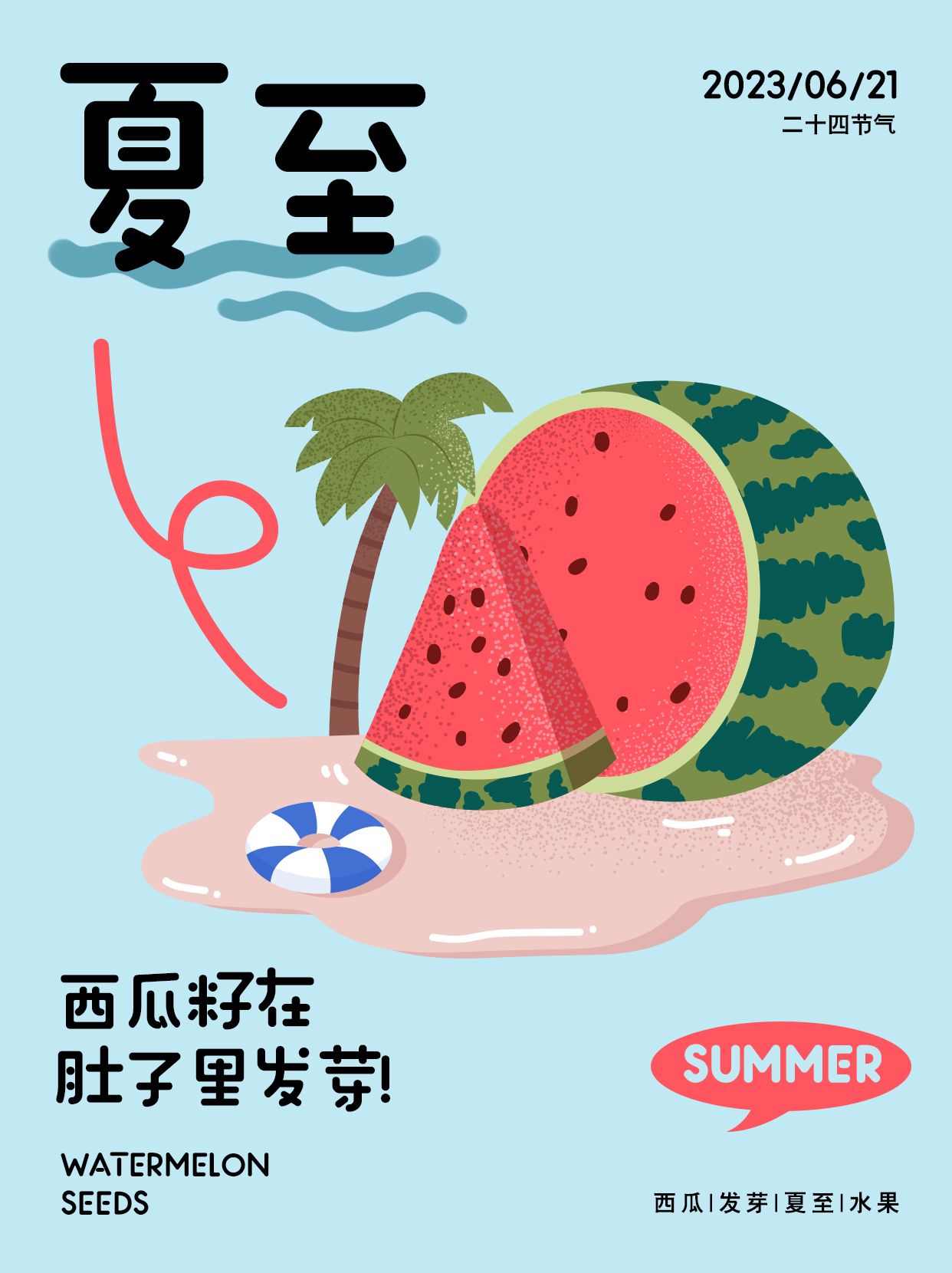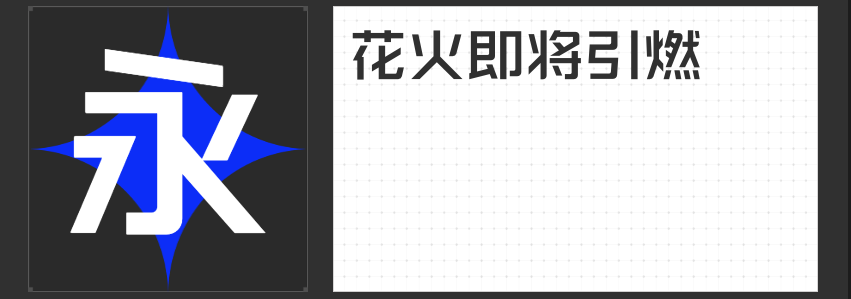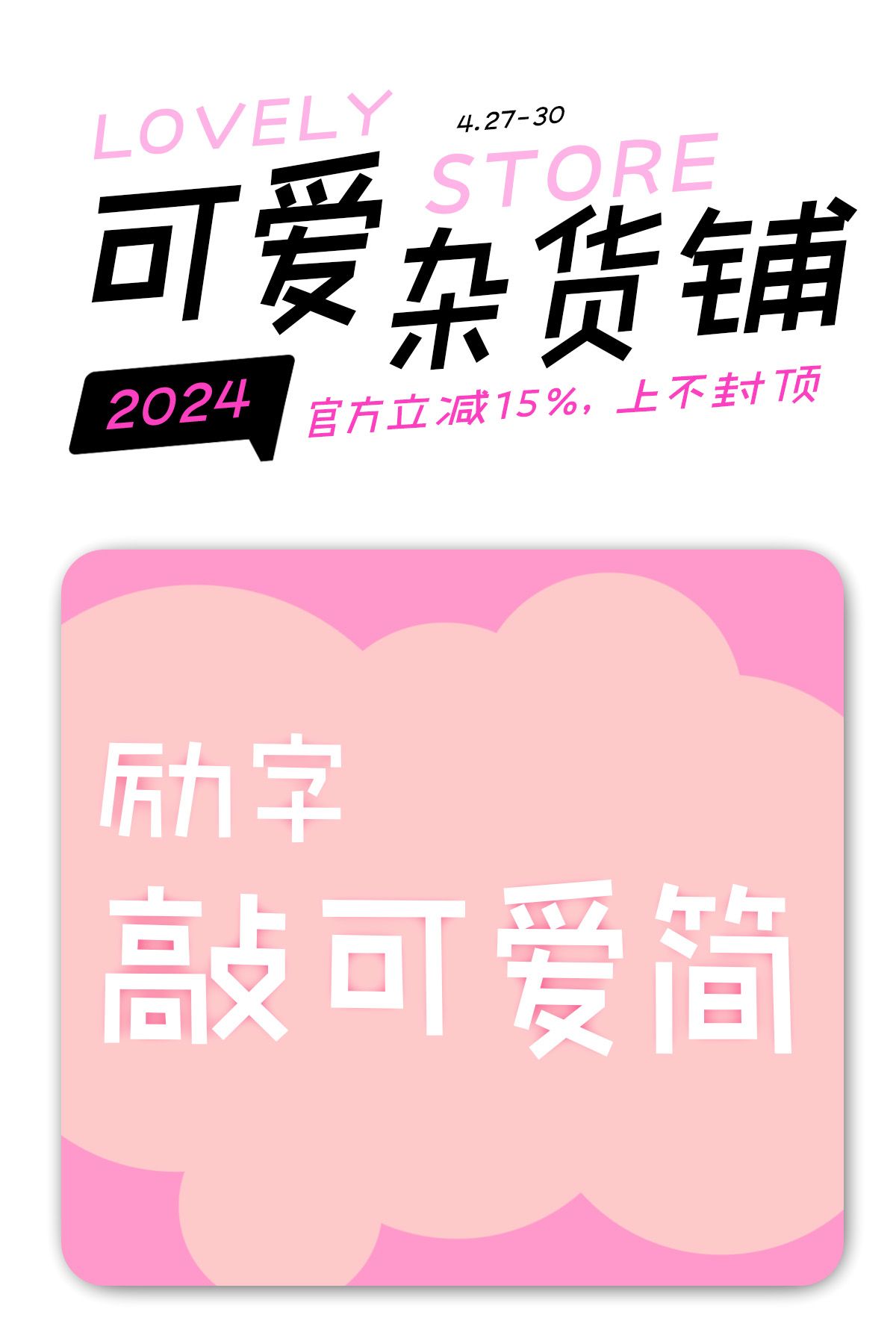
影视设计中的创意字体推荐:打造视觉盛宴的必备之选
在影视设计中,字体选择至关重要,它不仅影响着观众的阅读体验,更能营造出独特的视觉氛围。今天,我们为大家推荐四款专为影视设计而生的创意字体,它们各具特色,能够为影视作品增添无限魅力。
这款字体略带俏皮,充满趣味与想象。其手写的圆润线条在保留辨识度的前提下,省略了部分笔画,使得整体看起来简单明快,独具形式感。这种字体营造了一种用心书写的随性氛围,让影视作品中的文字更具手绘感和温暖度。无论是用于片头字幕、旁白还是角色对话,都能瞬间吸引观众的眼球。
这款字体笔划粗壮有力,没有衬线装饰,撇捺等笔画不尖,使得整体易于阅读且突出醒目。它常用于标题、导语和标志等场合,能够迅速抓住观众的注意力。在影视设计中,励字勇敢黑简 中黑不仅能够提升作品的层次感,还能增强视觉冲击力,让观众在观影过程中留下深刻印象。
这款字体拥有完美的斜度和利索的转折,保持了独特的个性。它摒弃了过度的装饰,加强细节的优化,降低了阅读障碍,为读者提供更加舒适的观影体验。全直线的设计符合当代视觉审美,使字体成为画面中的亮点。在影视作品中,励字钧线黑简 微黑能够营造出一种简洁、大气的氛围,让作品更加时尚、前卫。
这款字体以手写感为基础,字型上松下紧,重心略低,结构松弛灵活且变化多样。整体笔形圆润饱满、舒展流畅,给人一种轻松愉悦的感觉。统一的笔画设计和内外圆角兼备的折笔处丰富了视觉效果。在影视设计中,励字造桃气圆 大粗不仅能够提升作品的可爱度和亲和力,还能让观众在轻松愉快的氛围中享受观影过程。
以上四款字体各具特色,无论是俏皮可爱、粗壮有力、简洁大气还是圆润饱满,都能为影视设计增添独特的视觉魅力。选择适合自己的字体,让你的影视作品更加出彩!